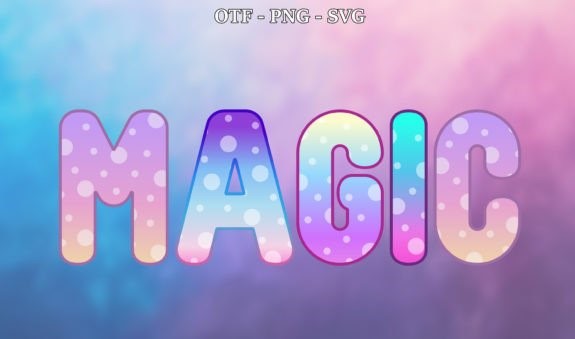
Magic Font
Magic Font – الخط السحري ✨????
اجعل تصاميمك تنبض بالحياة مع Magic Font – الخط الفريد الذي يجمع بين الأناقة والإبداع! ????
✔️ تصميم احترافي وأنيق يناسب جميع الاستخدامات
✔️ متعدد الاستخدامات لمشاريع التصميم، الشعارات، المحتوى الرقمي والمطبوعات
أضف لمسة سحرية إلى إبداعاتك واجذب الانتباه بأسلوب فريد! ✨????